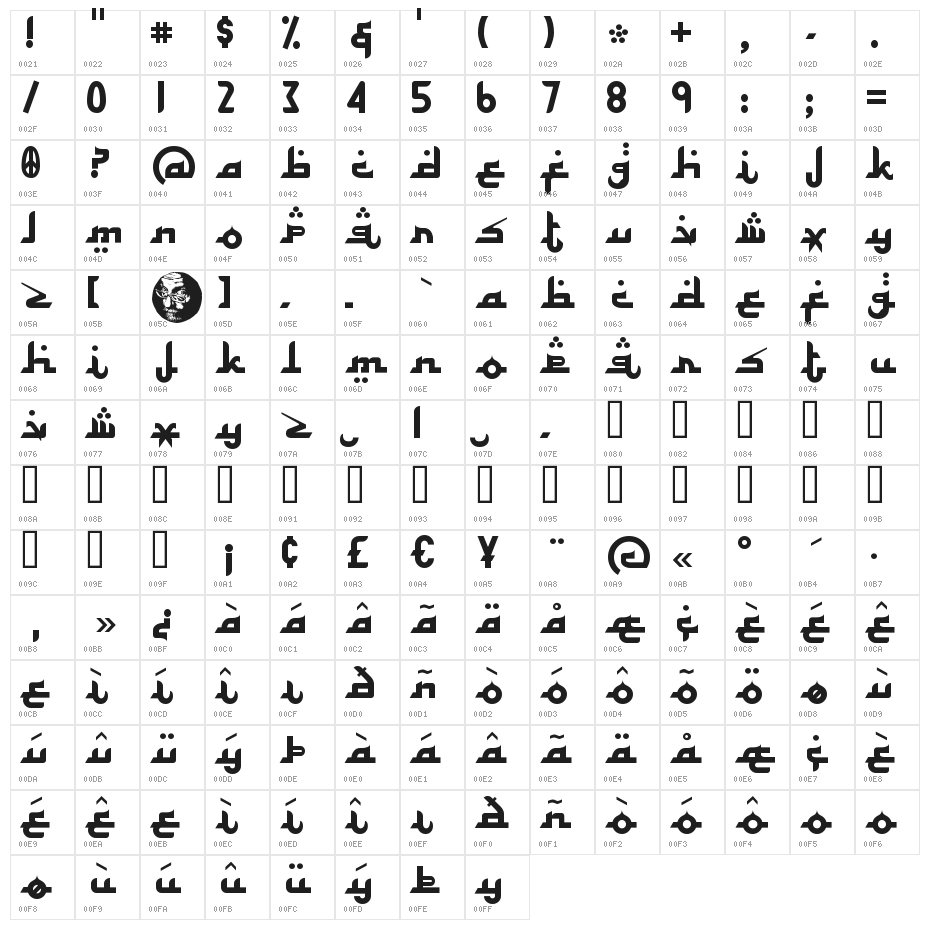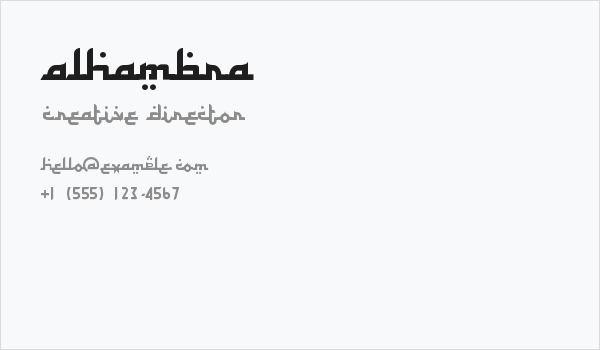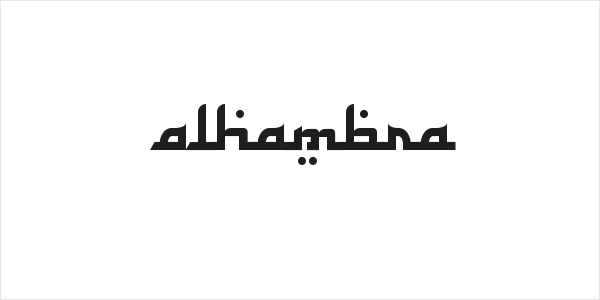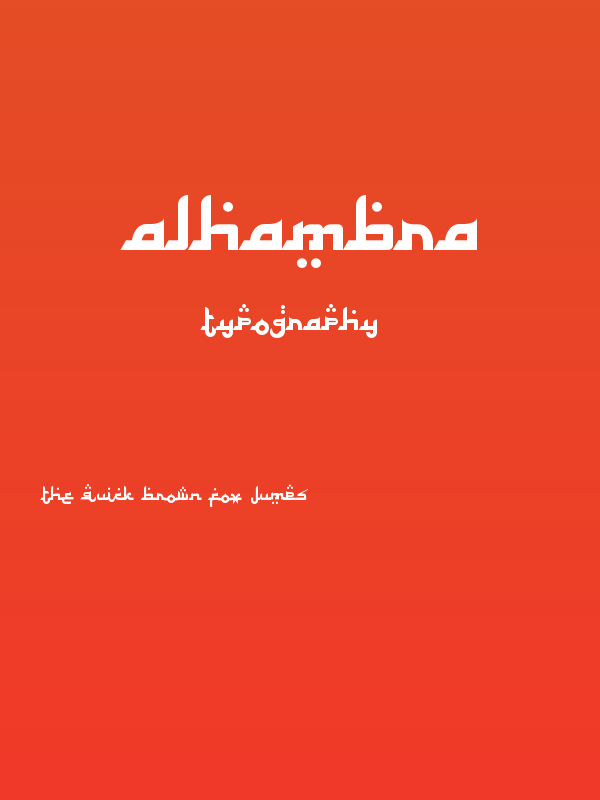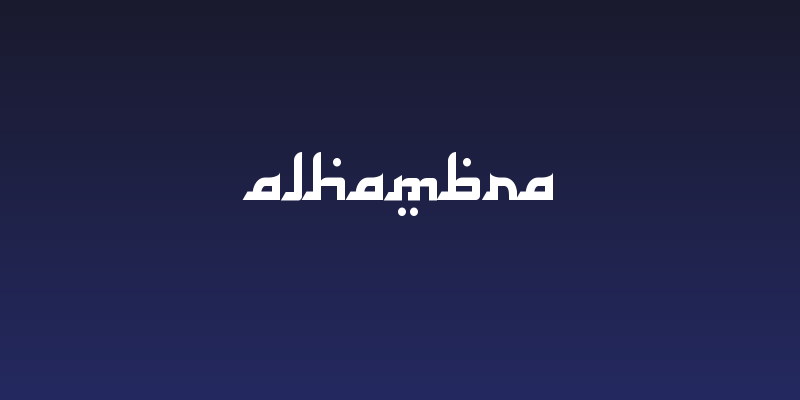
Alhambra Font
| Anwendungsfall | Logos, Headlines, Posters |
| Vorgeschlagene Projekte | Ideal for branding, posters, cultural events, and artistic projects requiring a unique and elegant touch. |